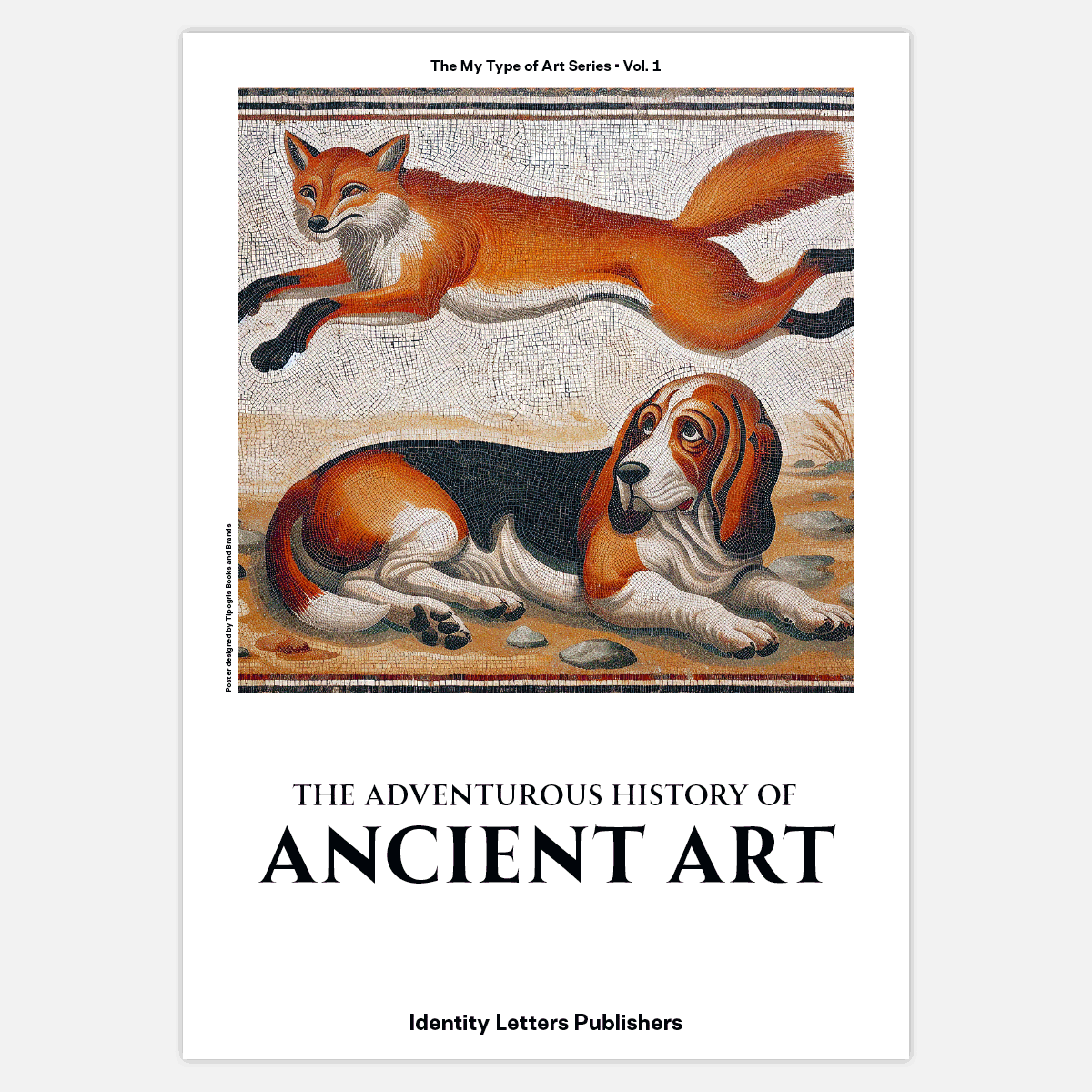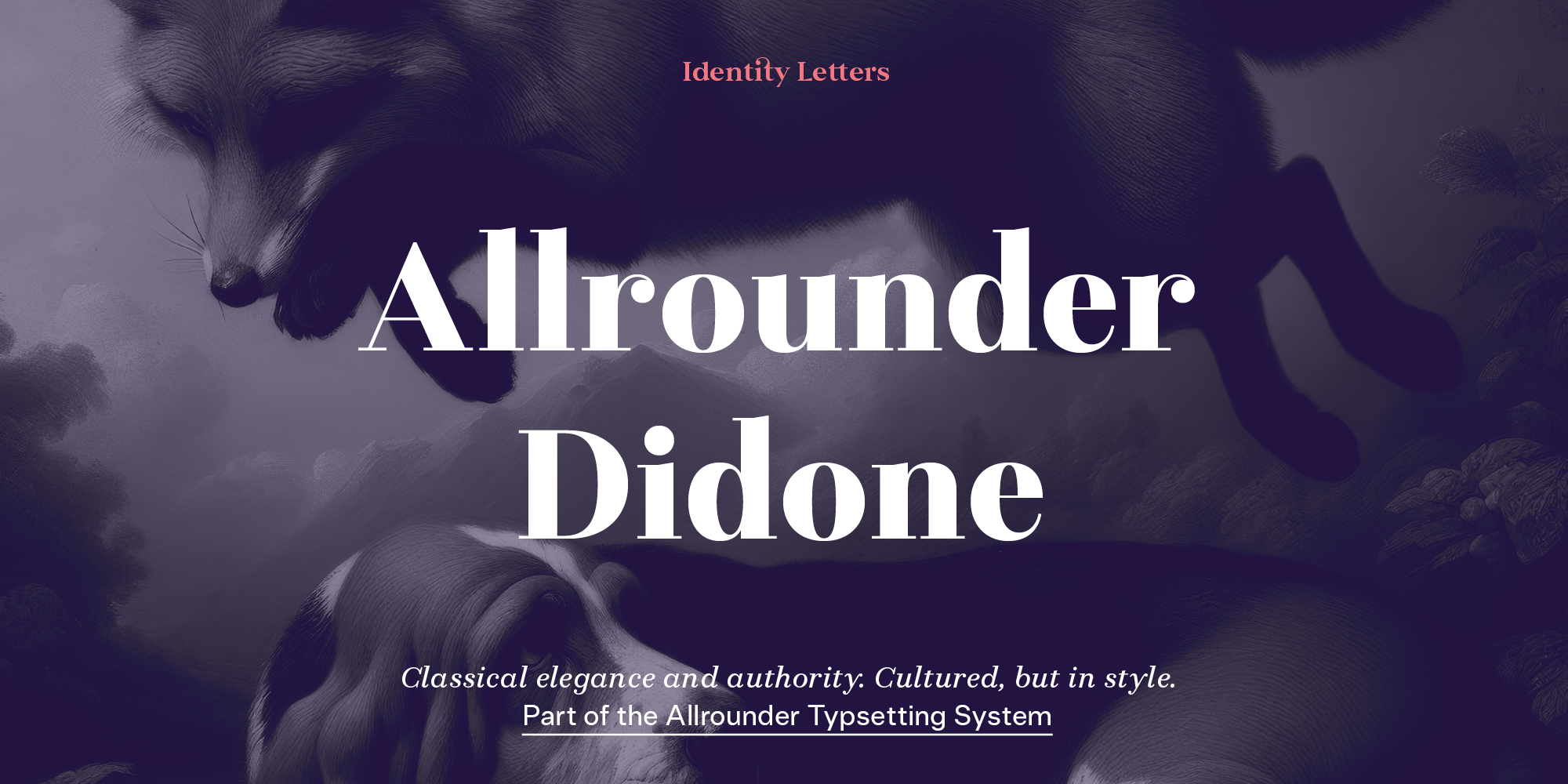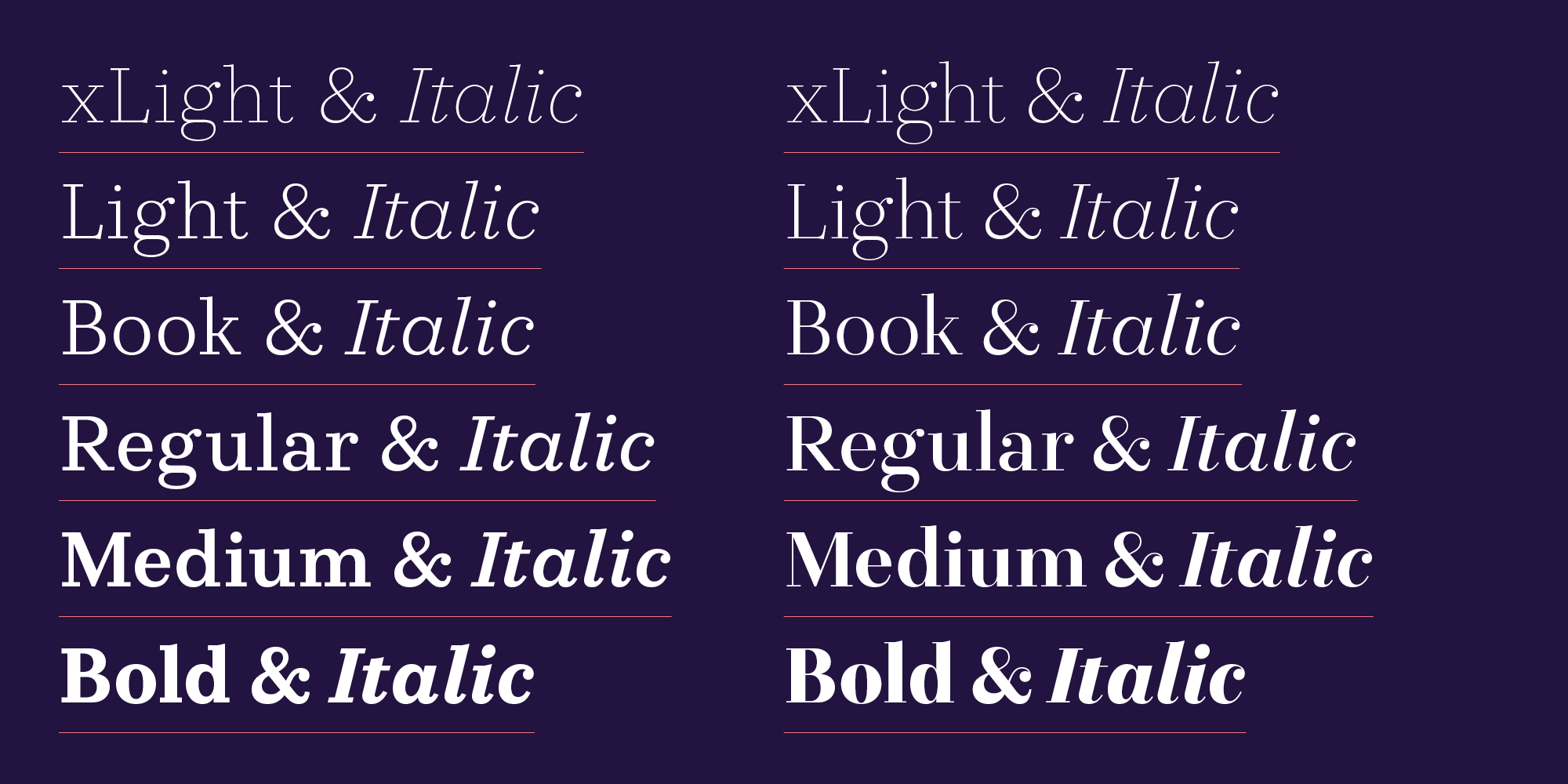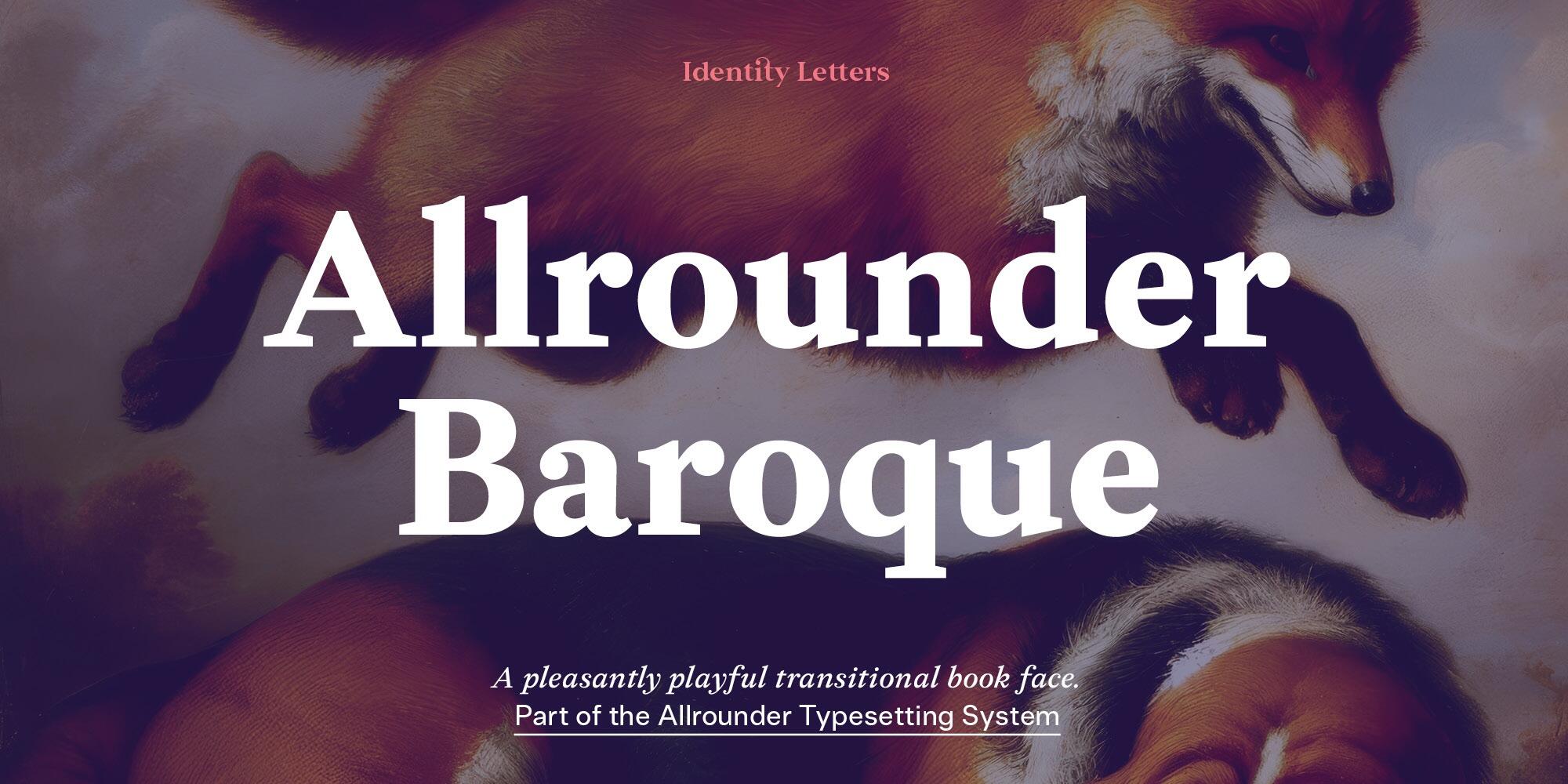
ich hab in der letzten Woche ein großes Update meiner Allrounder Collection veröffentlicht.
Neben einer  Überarbeitung der Allrounder Grotesk, Antiqua und Monument, habe ich außerdem neue Weiten (Condensed & Compressed) und eine Mono zur Grotesk hinzugefügt. Einen Blogartikel über die Änderungen gibt es hier.
P.s.: Die Didone wird im April veröffentlicht, die Baroque ist für den Herbst geplant.